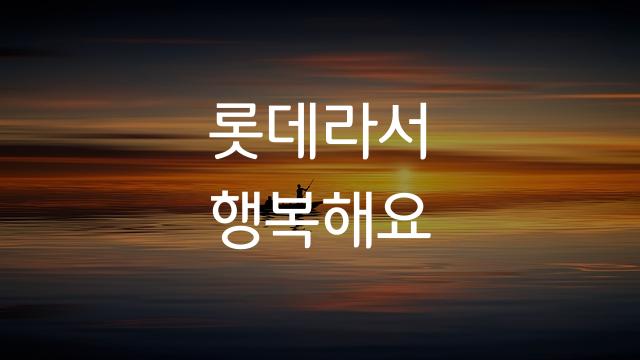
롯데마트행복체는 롯데마트와 헤움디자인이 협력하여 제작한 폰트로, 둥근 고딕 형태의 디자인이 특징입니다. 살짝 굴린 모양과 장식적인 요소가 포함되어 있어 따뜻하고 친근한 느낌을 줍니다.
롯데마트행복체은(는)
기본 고딕, 둥근 스타일, 장식 스타일, 감성적인, 부드러움, 복실복실, 별모양/패턴 계열의 생김새를 가지고 있으며
광고 캠페인, 제품 포장, 카페 메뉴 등에서 자주 활용되며, 효과적인 메시지 전달에 적합합니다.
이 폰트는 음식/식음료, 라이프스타일, 소매/유통 분야에 잘 어울리며,
따뜻한, 친근한, 편안한 느낌을 담고 있는 것이 특징입니다.